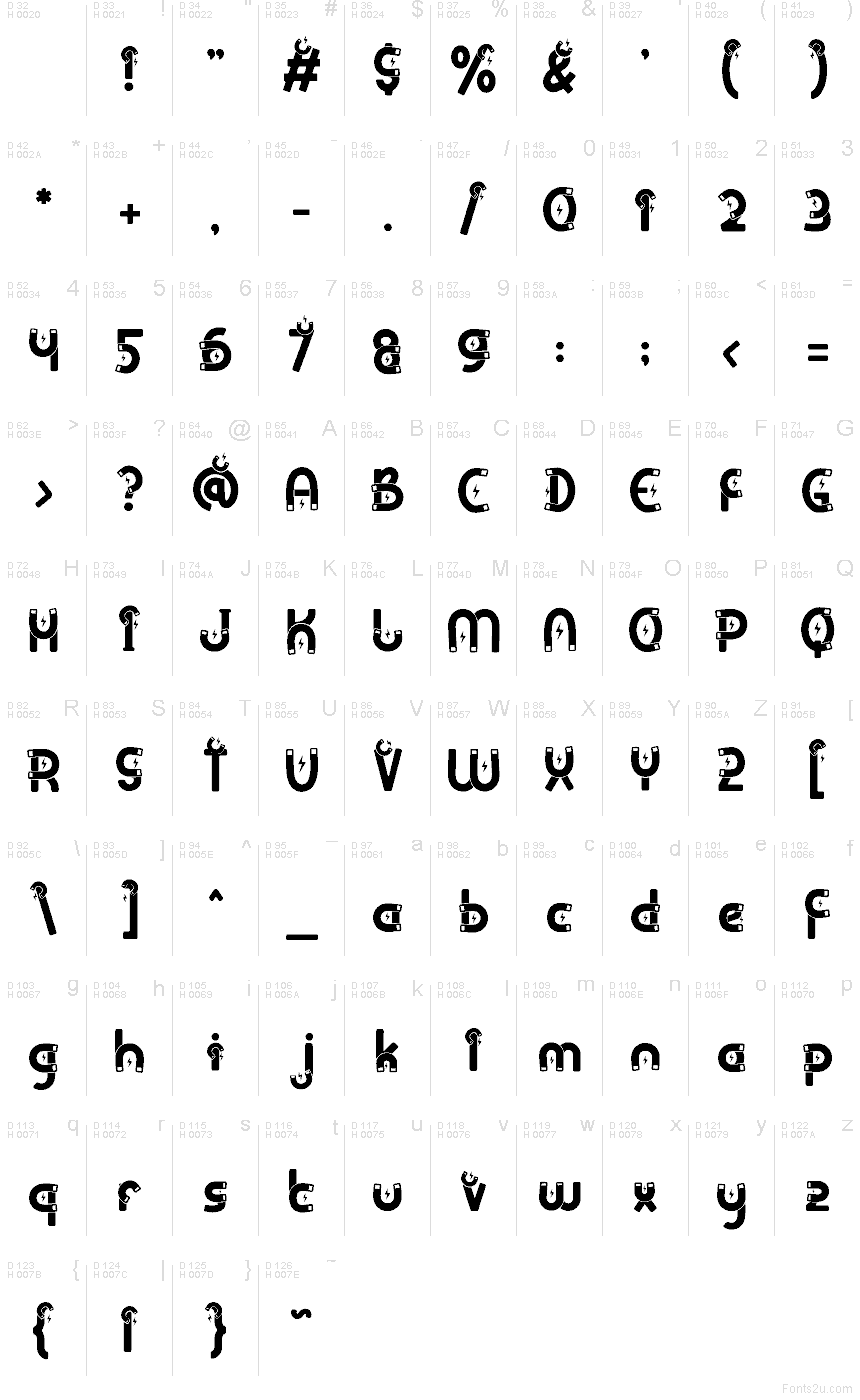
Clever Science Magnet
Clever Science Magnet von Putracetol Studio ist eine kostenlose Display-Schriftart, die Wissenschaft und Magnetismus spielerisch vereint. Mit ihren klobigen, abgerundeten Formen, die an klassische Schulmagnete erinnern, und kleinen, blitzartigen Akzenten wirkt sie gleichermaßen verspielt wie ein wenig nerdig. Die kräftigen, schwarzen Lettern, die abgeschrägten weißen Spitzen und das durchgehende Magnet-Motiv verleihen dem gesamten Alphabet ein eigenständiges Konzept statt nur dekorativem Beiwerk.
Die Schrift eignet sich hervorragend für Schulplakate, Flyer für Wissenschafts-Clubs, Experimentierkästen, Kinderbuchcover, Infotafeln für Messen oder Titel, bei denen das Design selbst das Thema unterstreicht. Als kostenlose Schriftart kommt sie am besten in kurzen Überschriften, Logos oder Beschriftungen zur Geltung, da die magnetischen Details hier als inhaltliches Element wahrgenommen werden und nicht als reine Dekoration.